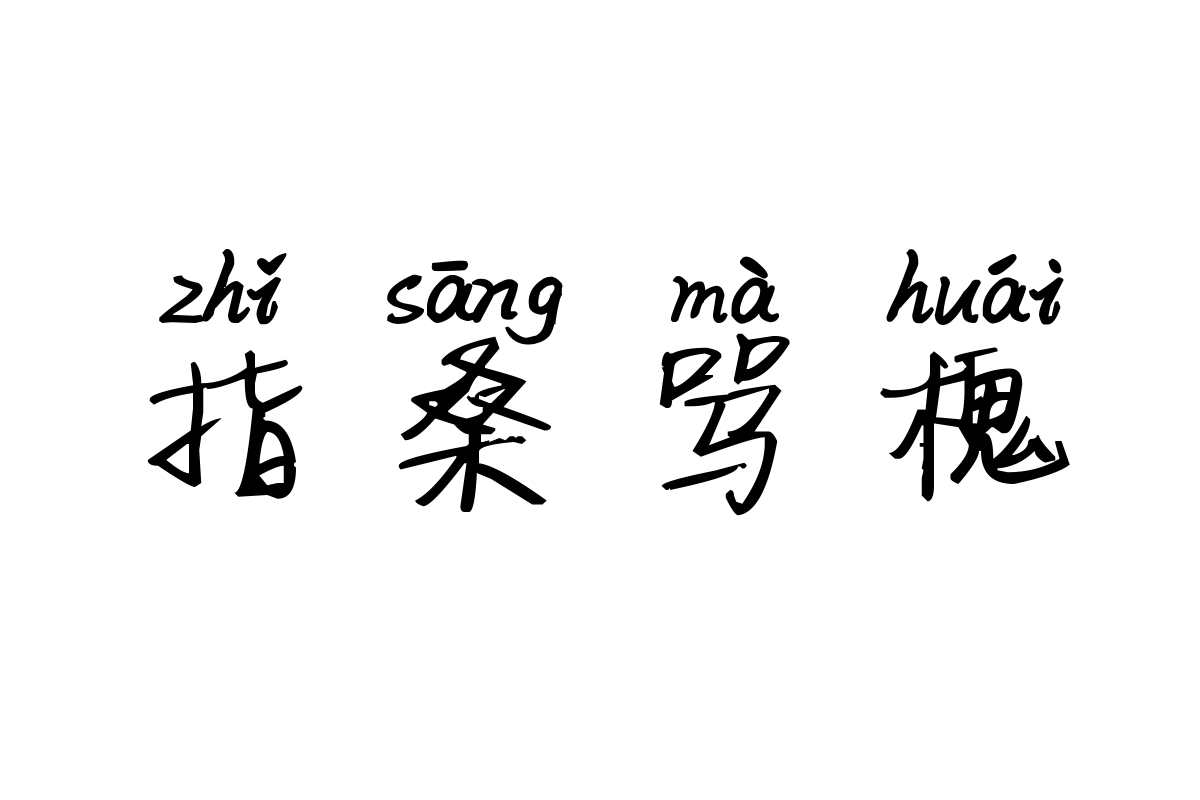
米开左耳情话拼音体是一种中文字体,它是由米开左耳设计团队开发的。这种字体的特点是采用了拼音的方式,使得阅读起来更加方便。
米开左耳情话拼音体的特点如下:
1. 字体风格独特,采用了拼音的方式,使得阅读起来更加方便。
2. 字体结构紧凑,笔画清晰,易于识别。
3. 字体颜色鲜艳,易于吸引眼球。
4. 字体大小适中,适合各种阅读场景。
5. 字体适用于各种印刷和电子媒体,如书籍、报纸、杂志、广告、网站等。
总之,米开左耳情话拼音体是一款实用且美观的中文字体,适合用于各种需要使用汉字的场合。